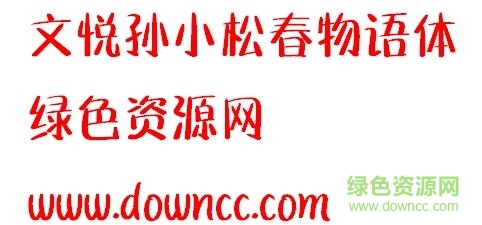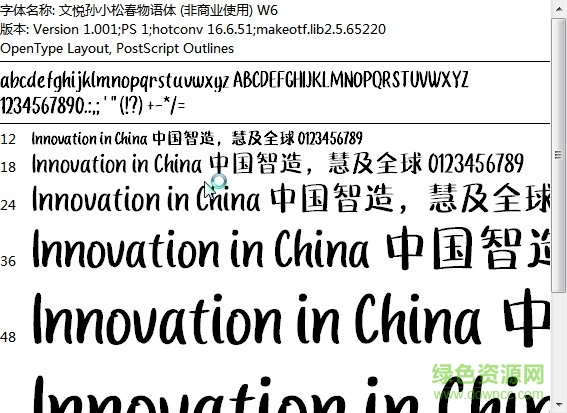
春物語(yǔ)體是文悅字庫(kù)設(shè)計(jì)師孫小松的新作,流暢的文字細(xì)膩的筆觸帶來不一樣的春光乍泄、生機(jī)勃勃的怡然體驗(yàn),給文字以生命力和活力,喜歡就來綠色資源網(wǎng)試試吧!
「文悅孫小松春物語(yǔ)體」采用2013年國(guó)務(wù)院公布、教育部、國(guó)家語(yǔ)言文字工作委員會(huì)組織制定的《通用規(guī)范漢字表》。
《通用規(guī)范漢字表》是一份較GB2312-80、GB12345-90更加適宜現(xiàn)代社會(huì)使用的常用字字符集標(biāo)準(zhǔn)。
孫小松春物語(yǔ)體是文悅2018手寫字體,兼具古籍文字和后現(xiàn)代印刷字體的藝術(shù)美感,更融合硬筆和毛筆書法的飄逸中正之氣,用作標(biāo)題、廣告等文字內(nèi)容都有很不錯(cuò)的藝術(shù)效果哦!